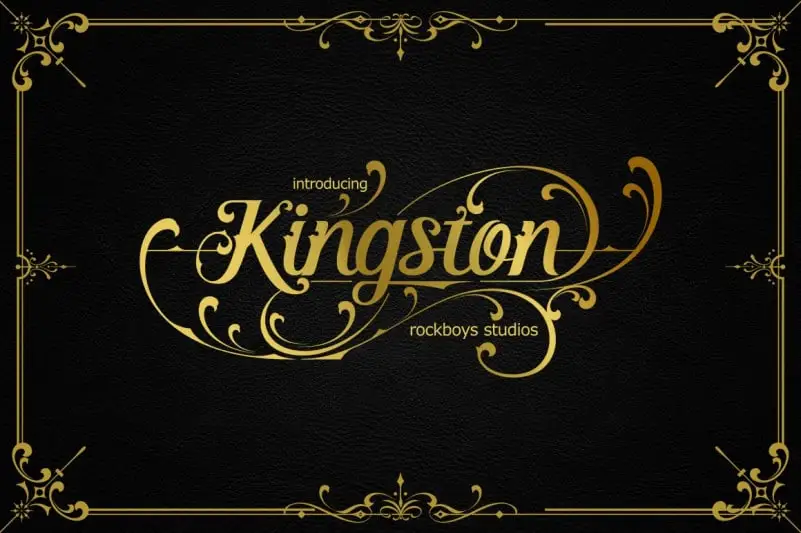
Kingston Blackletter Font – Download Grátis
A Kingston Blackletter Font é uma elegante seleção do estilo Blackletter que traz uma reviravolta moderna a esse gênero antigo. Esta font foi cuidadosamente projetada pela Dansdesign, e oferece um conjunto de ornamentações adoravelmente decorativas para facilitar o processo de criação de design vintage. Com essa combinação, você pode construir designs encantadores rapidamente em seu projeto. Estas letras são perfeitas para uso em logotipos de produtos, títulos e headlines em posters, embalagens, selos, cartões de aniversário para casamentos, logos de marcas de roupas, bem como design vintage. O grande mérito desta font é sua versatilidade. Ela se destaca não apenas pelo seu encanto antigo, mas também pela facilidade com que pode ser usada em uma ampla variedade de aplicativos gráficos. Essa font é tanto um elemento de beleza quanto uma ferramenta eficaz para a criação de logos, tags e embalagens que transmitam elegância e sofisticação. Além disso, oferece uma versão versátil que irá certamente atender aos seus mais variados projetos de design vintage.